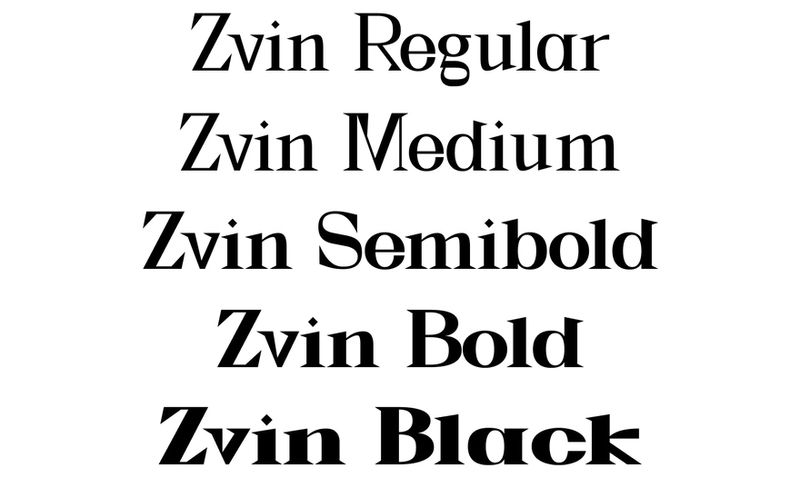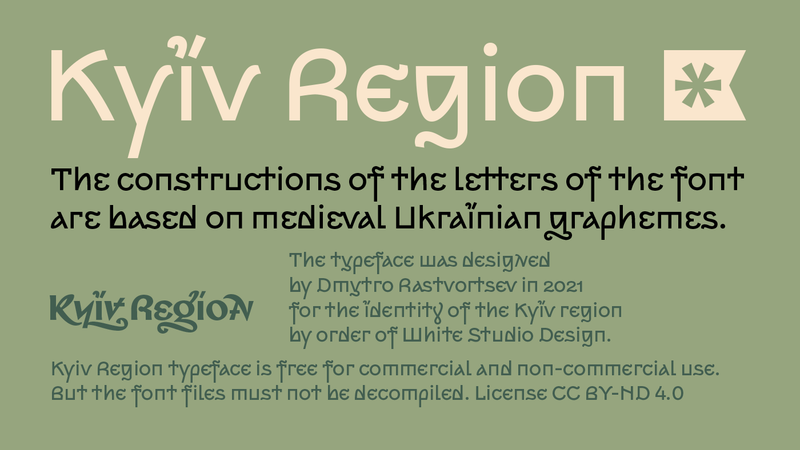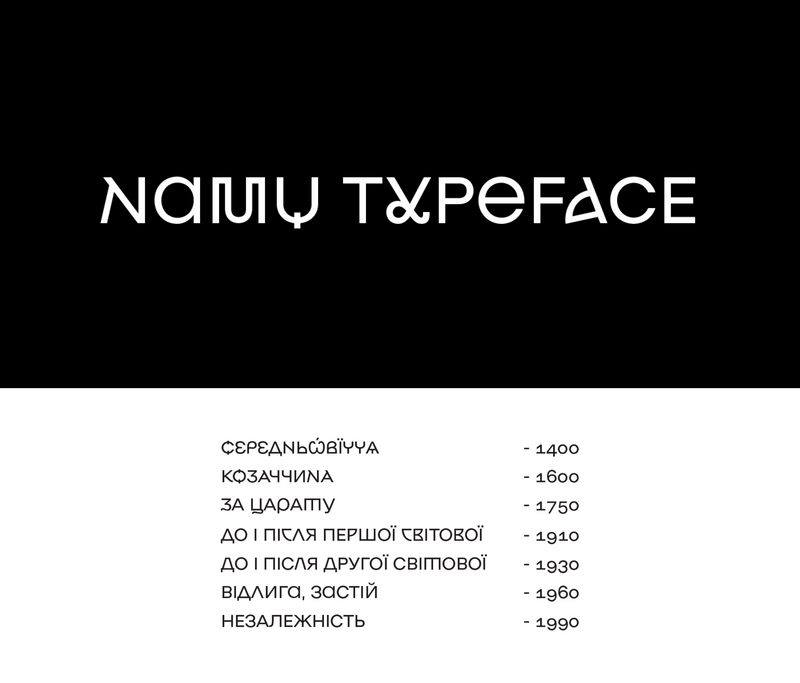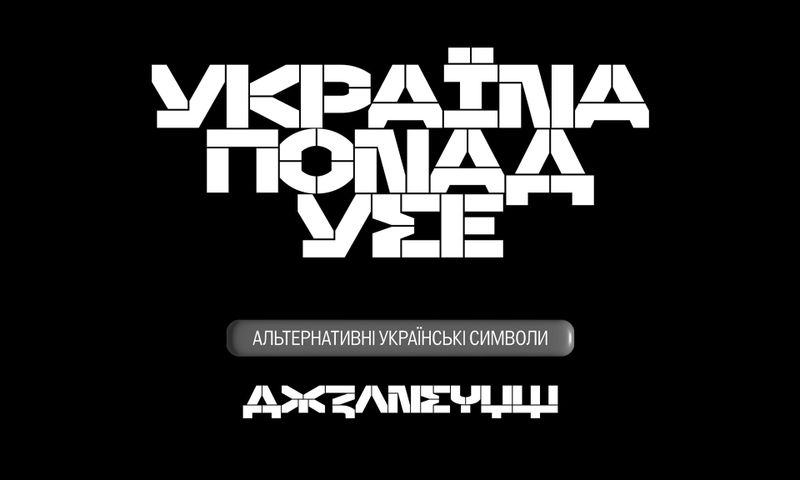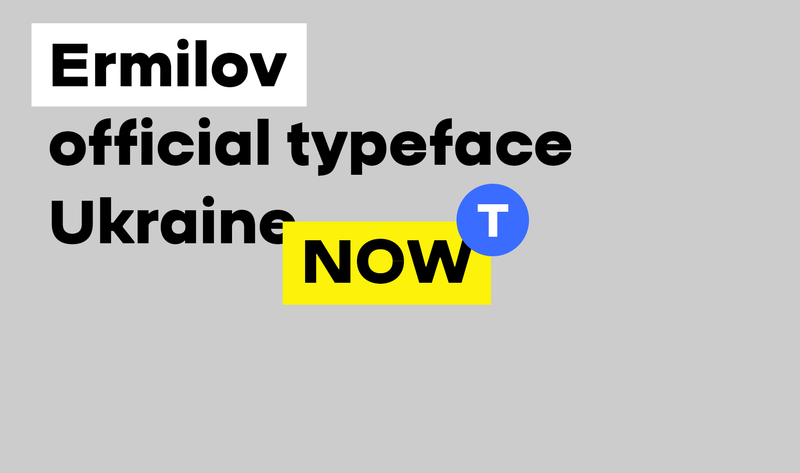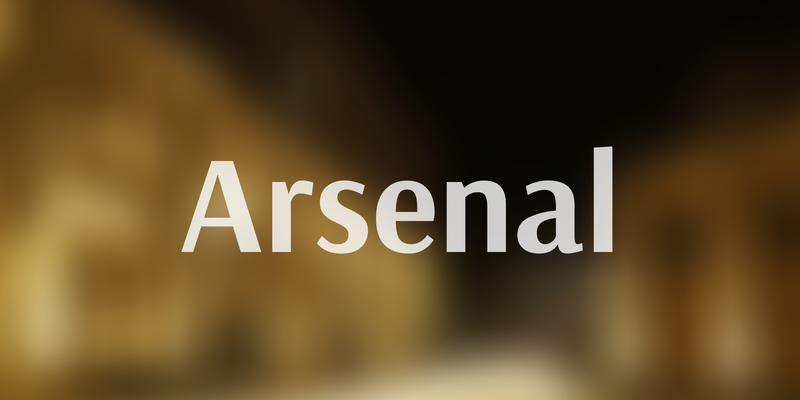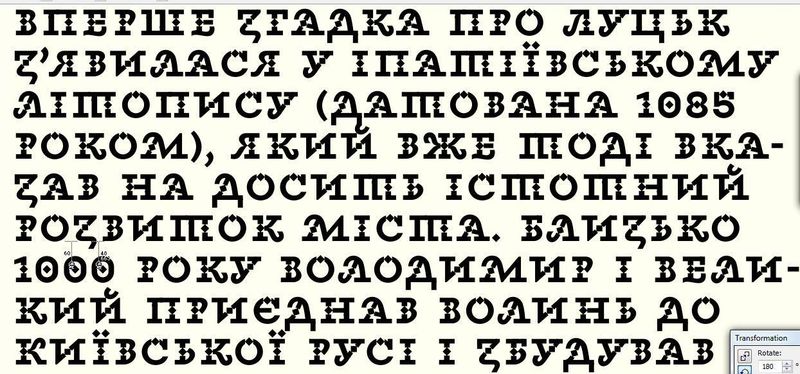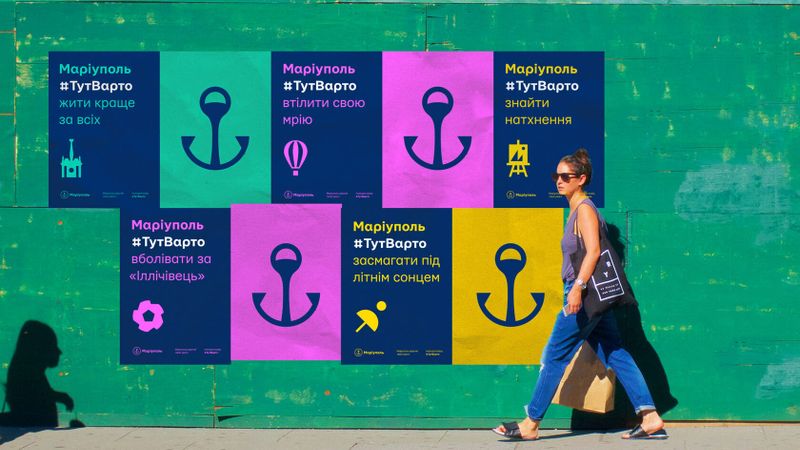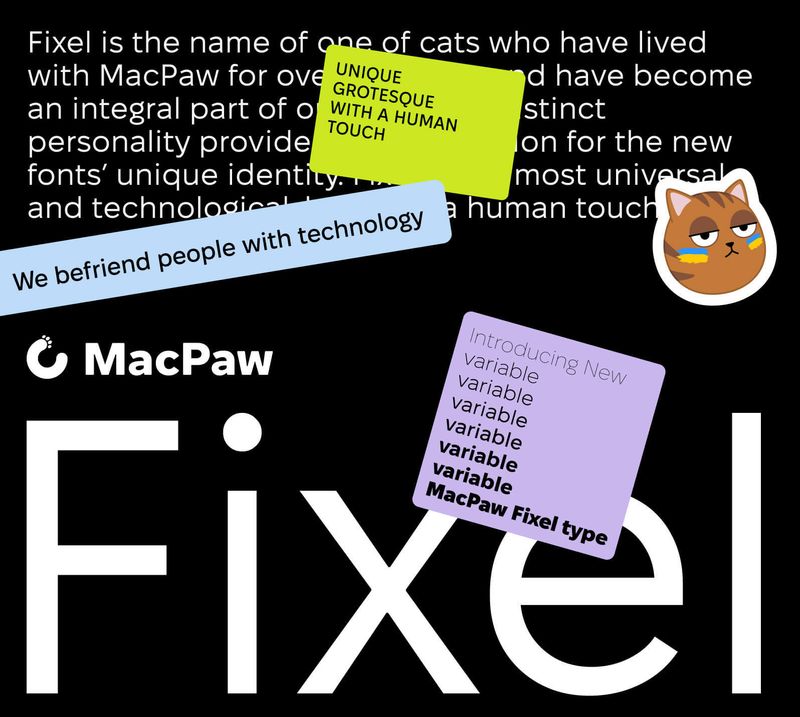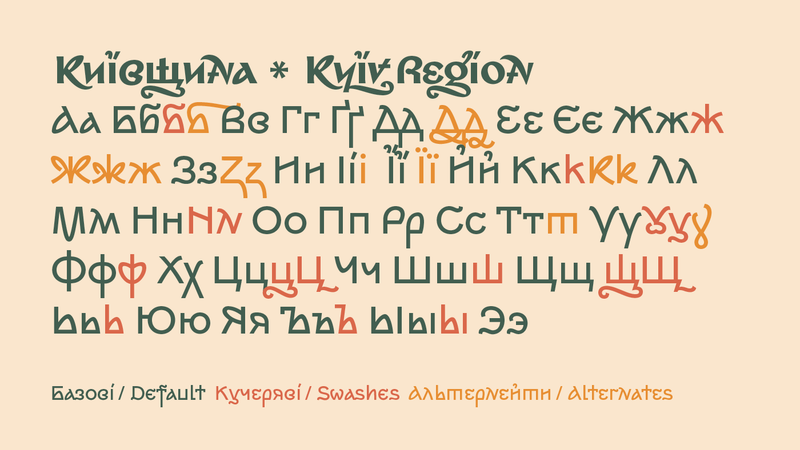
Die Kultur der ukrainischen Schriftarten
Die Kultur der ukrainischen Typografie blickt auf eine tiefe und geschichtsträchtige Historie zurück. Seit Jahrhunderten drücken Künstler ihre nationale Identität durch Schriftarten aus, und diese Tradition setzt sich bis heute fort. Die Nachfrage nach ukrainischen Kulturelementen wächst sowohl im Inland als auch international rasant.
Entdecken Sie eine kuratierte Sammlung kostenloser ukrainischer Schriftarten, die von talentierten Designern erstellt wurden. Von kräftigen geometrischen Stilen bis hin zu eleganten Serifenschriften – diese Fonts zelebrieren das reiche kulturelle Erbe und die moderne Kunstfertigkeit der Ukraine. Perfekt für Branding, Webdesign und kreative Projekte, unterstützt jede Schriftart die ukrainische Sprache und bietet einen einzigartigen Charakter, um Ihre Designs aufzuwerten. Laden Sie sie jetzt herunter und verleihen Sie Ihrer Arbeit einen Hauch ukrainischer Identität!
Nyght Serif: Eine kostenlose ukrainische Schriftart mit Open Font License
Die Schriftart unterstützt erweiterte lateinische sowie kyrillische Zeichen und konzentriert sich ausschließlich auf das ukrainische Alphabet, was sie zu einer ausgezeichneten Wahl für Designs macht, die die ukrainische Identität betonen.
- Autor: Maksym Kobuzan
Zvin Serif: Eine anspruchsvolle Schrift, inspiriert von historischer Typografie
Zvin Serif ist eine einzigartige Schriftart mit variablen Serifen, die ihre Inspiration aus der Typografie der Jahre 1850 bis 1960 schöpft. Ihre Stimmung und Dynamik basieren auf griechischen Buchstabenformen, die mit modernen dekorativen Stilen verschmolzen sind. Mit scharfen Winkeln und markanten Serifen ist Zvin Serif elegant und auffällig – perfekt, um jedem Design einen authentischen Charakter zu verleihen.
- Alphabet-Unterstützung: Lateinisch und Kyrillisch
Schriftschnitte: Regular, Medium, Semi-Bold, Bold
Autor: Ivan Tsanko-Khlibovych
Work Sans + Work Grotesk: Vielseitige serifenlose Schriftarten für das Web
Work Sans ist eine äußerst vielseitige serifenlose Schriftart, die speziell für die Verwendung im Web entwickelt wurde. Sie verfügt über einen Kernsatz lateinischer und kyrillischer Zeichen und ist somit ideal für moderne digitale Projekte, bei denen Klarheit und Lesbarkeit unerlässlich sind.
Zusammen mit Work Grotesk bietet diese Schriftfamilie eine umfassende Lösung für saubere und funktionale Web-Typografie.
- Autor: Ivan Tsanko-Khlibovych
Nastup Basic: Eine kostenlose modulare Schablonenschrift mit technischem Touch
Nastup Basic ist eine kostenlose, modulare serifenlose Schablonenschrift, die von technischen Schablonenbeschriftungen an Wänden und Konstruktionsdetails inspiriert ist. Der Name „Nastup“ bedeutet auf Ukrainisch „Vormarsch“ und spiegelt ihre kühne und industrielle Ästhetik wider.
Mit minimalem Zeichenabstand eignet sie sich außergewöhnlich gut für schmale Layouts, insbesondere bei engem Zeilenabstand. Designer können auch durch die Verwendung alternativer breiter oder offener Zeichen für Abwechslung sorgen. Nastup Basic unterstützt erweitertes Latein, grundlegendes Kyrillisch, griechische Alphabete und verfügt über einen alternativen Zeichensatz, der speziell auf das ukrainische Alphabet zugeschnitten ist.
- Autor: Maksym Kobuzan
Kyiv Region Typeface: Eine kostenlose Schrift, die Geschichte und Moderne vereint
Die Kyiv Region Typeface ist eine originelle, kostenlose Schriftart, die speziell für das territoriale Branding der Oblast Kiew entwickelt wurde. Erstellt von White Studio Design, verbindet sie meisterhaft historische Tiefe mit avantgardistischem Experimentieren.
Die Schriftart greift auf Halbunzial- und Kursivformen zurück, die typisch für die Kiewer Rus und die Epoche des ukrainischen Barocks sind, und vermischt sie mit dem geometrischen Konstruktivismus des 20. Jahrhunderts – einem Stil, der eine moderne Wiederbelebung erfährt.
Das Ergebnis ist eine zeitgenössische geometrische serifenlose Schriftart mit Strichen, Alternativzeichen, Ligaturen und historischen Formen. Sie eignet sich perfekt für thematische Beschilderungen, Werbung, Verpackungen, Souvenirs und sogar für kirchenslawische historische Texte.
- Autor: Dmytro Rastvortsev
Irpin Type: Eine kühne Hommage an die Stadt Irpin
Irpin Type ist eine einzigartige Schriftart, die vom Geist der Stadt Irpin inspiriert ist. Sie ist für den vielseitigen Alltagsgebrauch konzipiert und eignet sich für Bücher, Logos, Corporate Branding, Poster und Präsentationen, bei denen ein mutiger und selbstbewusster Eindruck erforderlich ist.
Die Mariupol Typeface wurde von Andriy Shevchenko speziell für das Branding von Mariupol entworfen. Diese geometrische Groteskschrift ist von Plakatgrafiken und modernen universellen Schriftarten inspiriert und kombiniert eine kühne Ästhetik mit funktionaler Vielseitigkeit. Sie spiegelt den zeitgenössischen und dynamischen Geist der Stadt wider und ehrt gleichzeitig ihre einzigartige Identität.
- Autor: Andriy Shevchenko